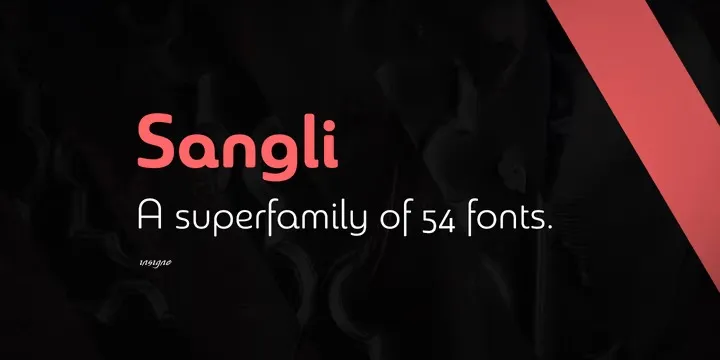
A fonte Sangli é uma sans serif que surge de um design humanista do tipo serif, adotando uma paleta moderna. Cada uma das fontes difere significativamente nas formas dos terminais de estroma, criando variedades únicas e atraentes. A versão original foi extremamente bem recebida, e dois anos depois surgiu uma revitalização e remasterização da Chennai, acompanhada por novas pesos e recursos OpenType inovadores. A Sangli é um excelente complemento para criações visuais contemporâneas, oferecendo uma aparente simplicidade com detalhes atraentes que tornam essa fonte perfeita para uso em qualquer projeto moderno ou digital. Engane-se se pensa que ela é apenas uma sans serif tradicional; o design de terminais inovadores dá à Sangli um toque único e contemporâneo, garantindo que ela seja tanto versátil quanto estilosa.